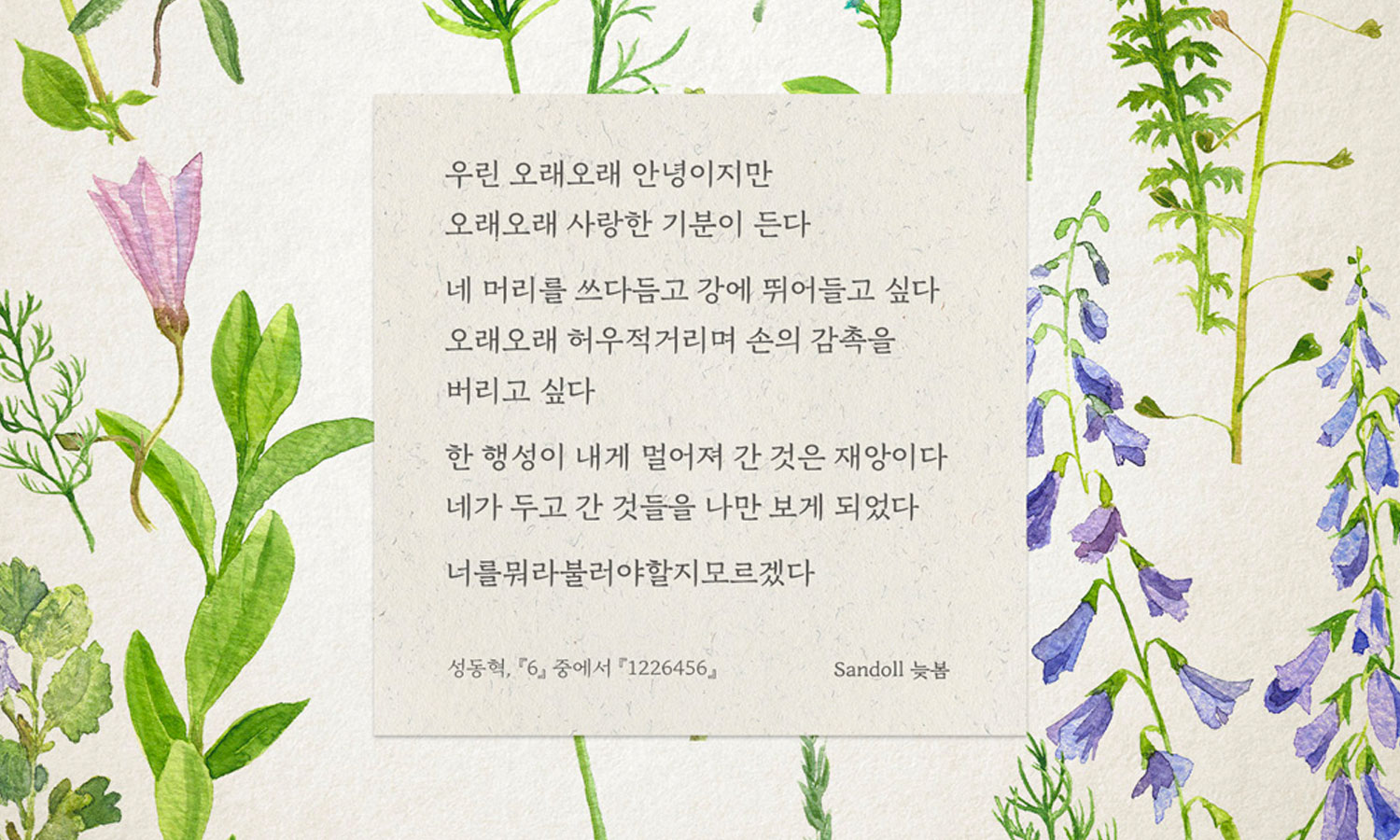
- 산돌 늦봄은 붓글씨 특유의 감성을 살리면서도 기존의 명조와는 분명한 차이점이 있는 본문용 폰트이다.
자연스러운 획의 꺾임과 손글씨의 필순을 따른 디자인, 정갈하고 부드러운 맺음 등이 특징이며 시, 브로슈어, 팜플렛, 광고의 바디 카피 등에 사용하면 특유의 감성을 잘 살릴 수 있다.
폰트 정보 폰트명 Sandoll 늦봄 / Sandoll LateSpring 구분 명조 폰트디자인 구모아, 박지인 디자인디렉팅 최성우 글자구성 한글 2,350자